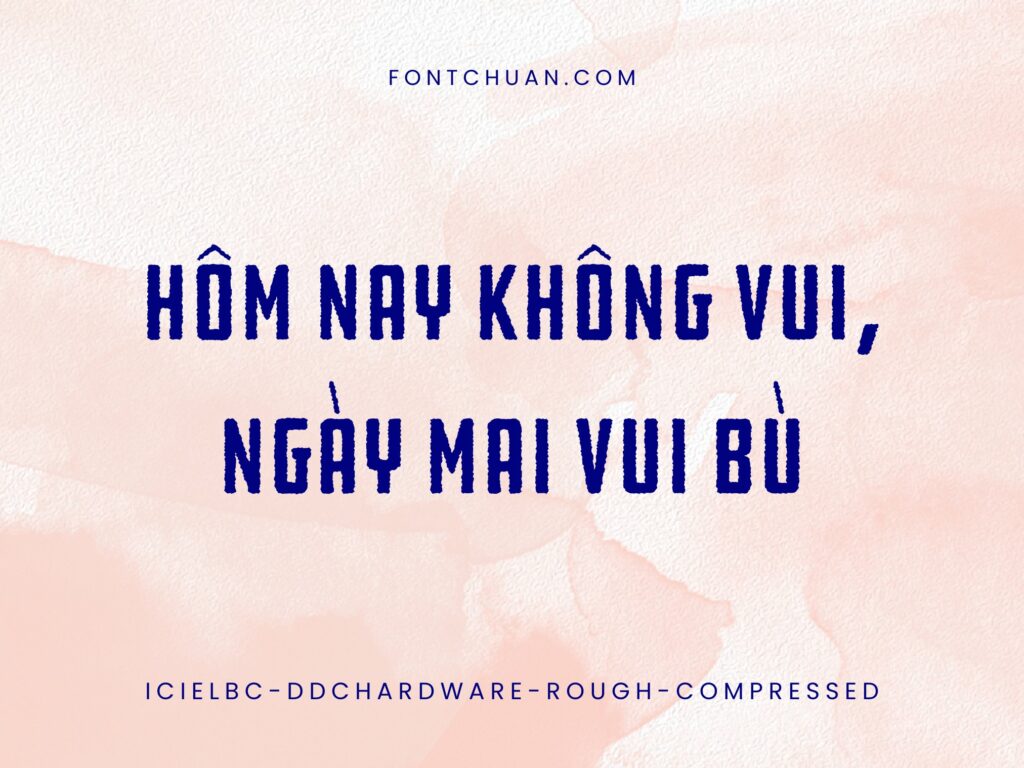
Font iCiel Bcddc Hardware Rough Việt Hóa
BCDDC Hardware Rough Compressed là một font chữ sans-serif đậm nét, mang phong cách công nghiệp với thiết kế góc cạnh và mạnh mẽ. Được thiết kế bởi Aaron James Draplin và Riley Cran, font này thuộc họ DDC Hardware, nổi bật với các ký tự in hoa và đường nét chắc chắn, tạo sự thu hút mạnh mẽ trong các thiết kế. Để hỗ trợ cộng đồng thiết kế Việt Nam, Iciel đã Việt hóa font BCDDC Hardware Rough Compressed, giúp font này hỗ trợ đầy đủ tiếng Việt cùng hơn 100 ngôn ngữ khác. Phiên bản BCDDC Hardware Rough Compressed Việt hóa đã được thành viên Font Chuẩn sưu tầm và đăng tải, mang đến sự lựa chọn đa dạng cho các nhà thiết kế.
Về đặc điểm thiết kế, BCDDC Hardware Rough Compressed sở hữu các ký tự in hoa với nét chữ đậm và góc cạnh, tạo nên sự cân đối giữa tính mạnh mẽ và sự hiện đại. Font này rất phù hợp cho các thiết kế như tiêu đề, poster, logo, bao bì sản phẩm và các dự án cần sự nổi bật. Ngoài ra, BCDDC Hardware Rough Compressed cũng là lựa chọn lý tưởng cho các ngành nghề như quảng cáo, bất động sản, giáo dục và công nghệ, mang lại phong cách chuyên nghiệp và hiện đại. Font này cũng thích hợp để sử dụng trong các sự kiện như lễ hội, sinh nhật và các dịp đặc biệt khác.